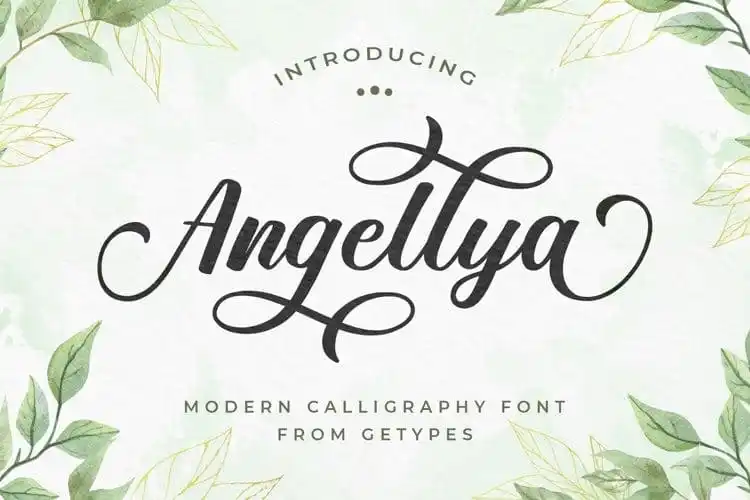
Angellya Calligraphy Font – Download Grátis
A Angellya Calligraphy Font é uma experiência visual única que une o clássico com o moderno. Manufacturada pela Getypes Studio, essa fonte destaca-se com um estilo elegante e sofisticado. Suas letras contêm elementos imperfeitos, com arranjos dinâmicos que lembram danças, proporcionando uma aparência suave, limpa e simples. É perfeitamente adaptável para qualquer projeto devido à sua rica funcionalidade. A alternância estilizada e as ligaturas tornam essa fonte especialmente atraente, criando um ambiente visual sofisticado. Seja em gráficos publicitários ou editoriais, a Angellya Calligraphy Font oferece uma maneira singular de destacar seu trabalho.